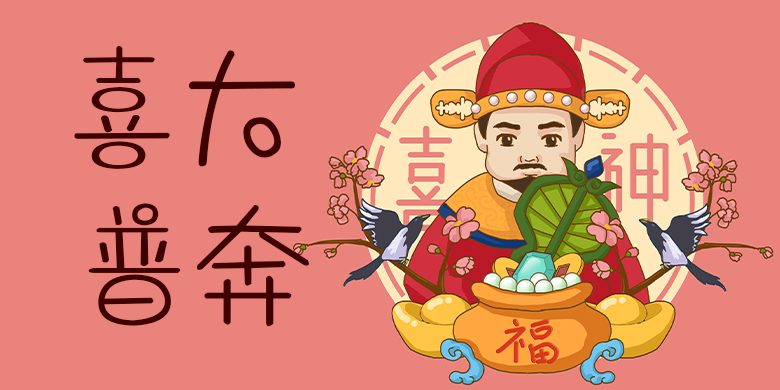
方正手迹-喜大普奔
字体品牌: 方正手迹 设计师:孙健营 字体分类:圆体、创意书写 字体属性:精品字 字符集:大陆简体(GB2312-80) 发布时间: 2020
喜大普奔体,这款大量的使用圆形元素,口、日等封闭空间都处理为圆形,一些点画也巧妙处理为小圆圈,大量部件与圆圈搭配使用,显得欢喜普奔,喜气洋洋。适用于儿童类的书刊、品牌广告和产品包装设计,以及社交网络的个性化用字。